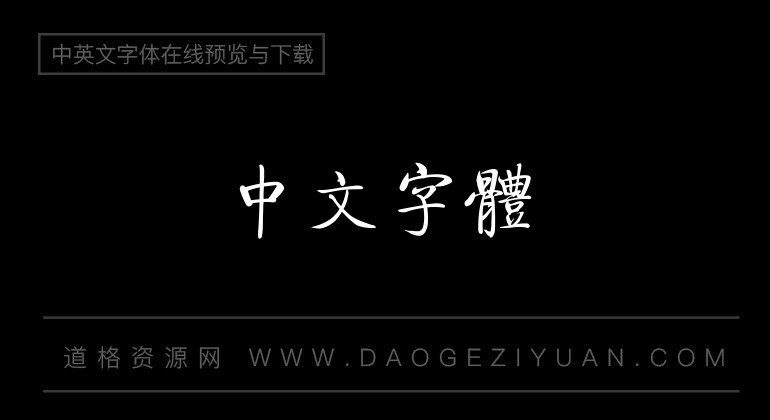
? 迷你繁启体是一款由繁体字改良而成的字体,它拥有繁体字的精致细腻,又有西文字体的舒适易读,是一款极具特色的字体。迷你繁启体字体采用稍微细腻的笔画,拥有比普通繁体字更精致的细节,让文字更加精致,更具有艺术感,适合用于各类品牌设计、海报设计、手绘图案等。文件名:MiNiFanQiTi-1.ttf
迷你繁启体是一款非常不错的手写艺术字体,具有很好的视觉感,适合于文化类的宣传设计、商业类品牌的广告和产品包装设计以及个性化文字排版等较多场景。